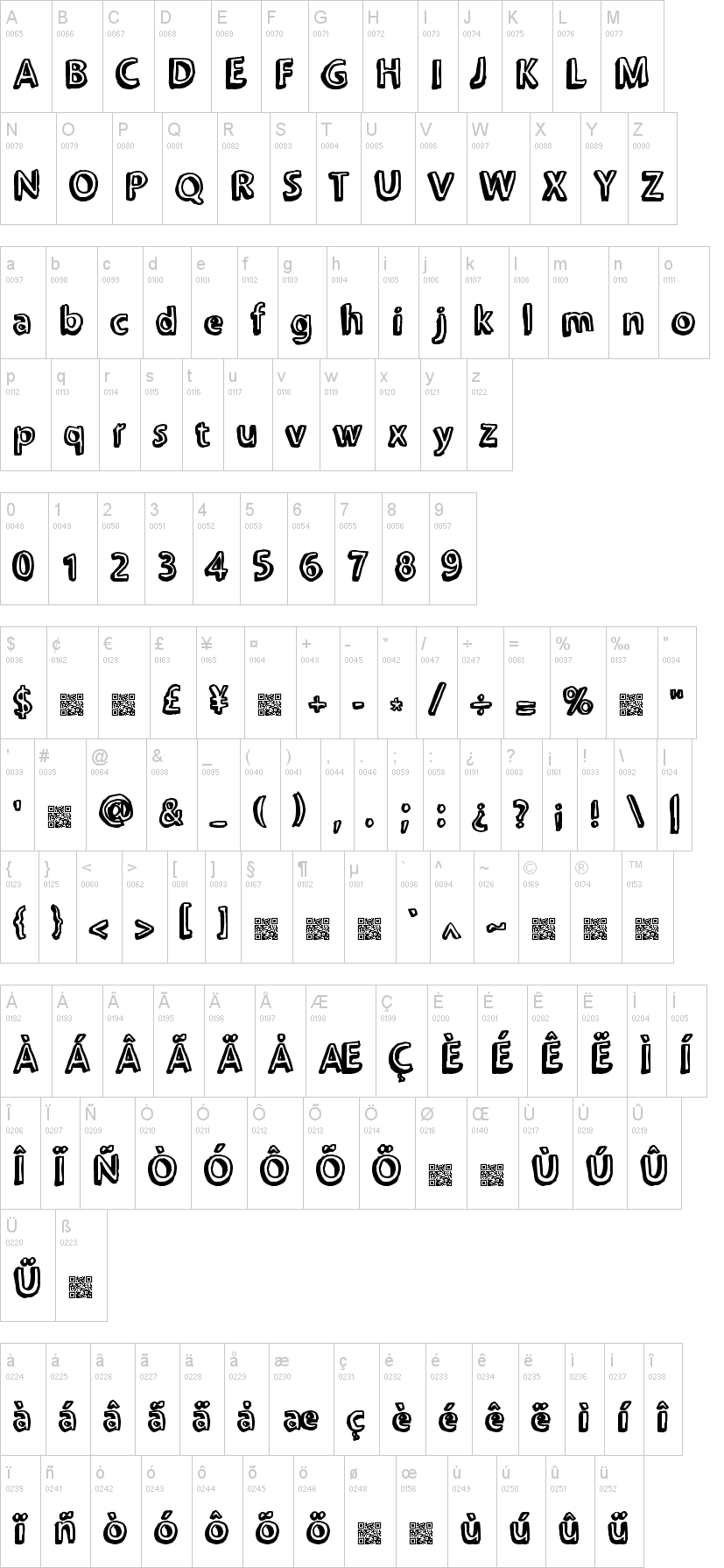
Chonkies
Chonkies 字体是一款源自西班牙的手写体字体,由设计师Juan Casco设计。它具有柔和、温暖的气息,是一款非常适合用于活泼、友善的设计中的字体。它的特点是可以让设计师自由发挥,把文字转化为任何想要的形状,可以轻松地创作出自己独特的设计。
Chonkies是一款非常不错的手写艺术字体,具有很好的视觉感,适合于文化类的宣传设计、商业类品牌的广告和产品包装设计以及个性化文字排版等较多场景。
Chonkies字符映射图